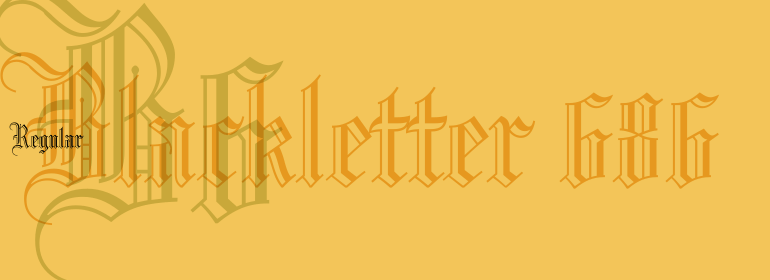
Blackletter 686
Blackletter 686,这款字体结构工整、笔画清晰,兼顾美观与易读性,适用于标题、正文、海报、包装、LOGO 等多种场景。字形优雅稳定,风格百搭耐看,适配日常排版与创意设计,让文字呈现更舒适、更具质感。Blackletter 686一笔一画,皆是细节,以均衡的比例、流畅的线条打造舒适视觉体验,字形端正大气,风格简约现代。无论是商业设计、品牌宣传还是日常排版,都能轻松驾驭,让文字更有格调与力量。Blackletter 686字体下载。